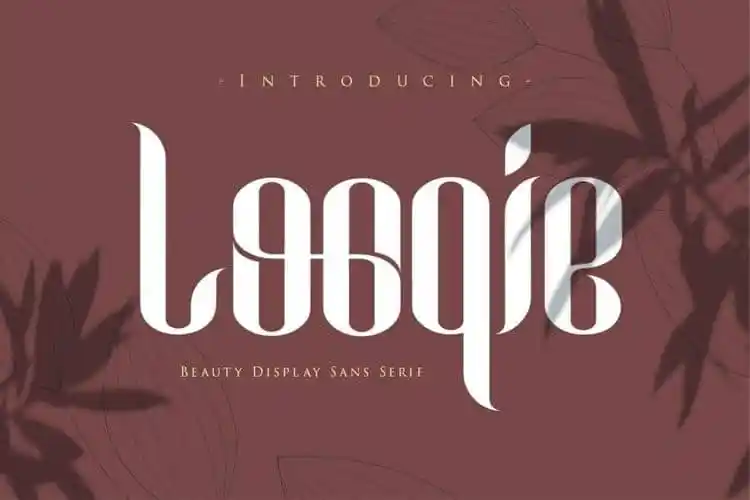
A Looqie Display Font é uma fonte sans-serif bold criada pelo Gilar Studio com ligaturas belas e suporte multilíngue. Desenvolvida para uso nas marcas de moda, sites de e-commerce, blogs sobre tendências ou boutiques de casamentos, ela oferece um toque sofisticado ideal para qualquer negócio que deseja criar uma aparência elegante. Testem o grande leque de previsões disponibilizadas e inspire-se, como eu fui enquanto criava essa fonte. Looqie é a escolha perfeita para quem busca dar ao seu negócio um aspecto impecável.